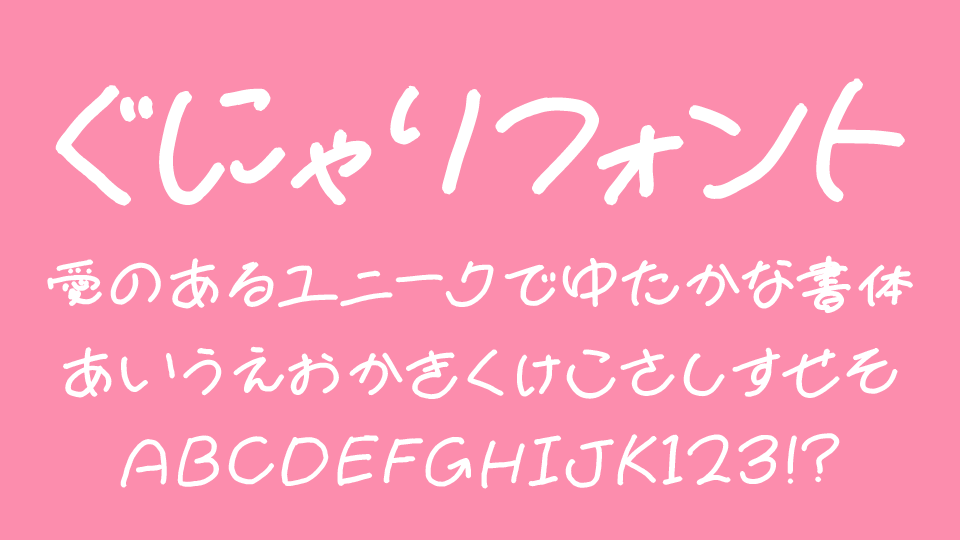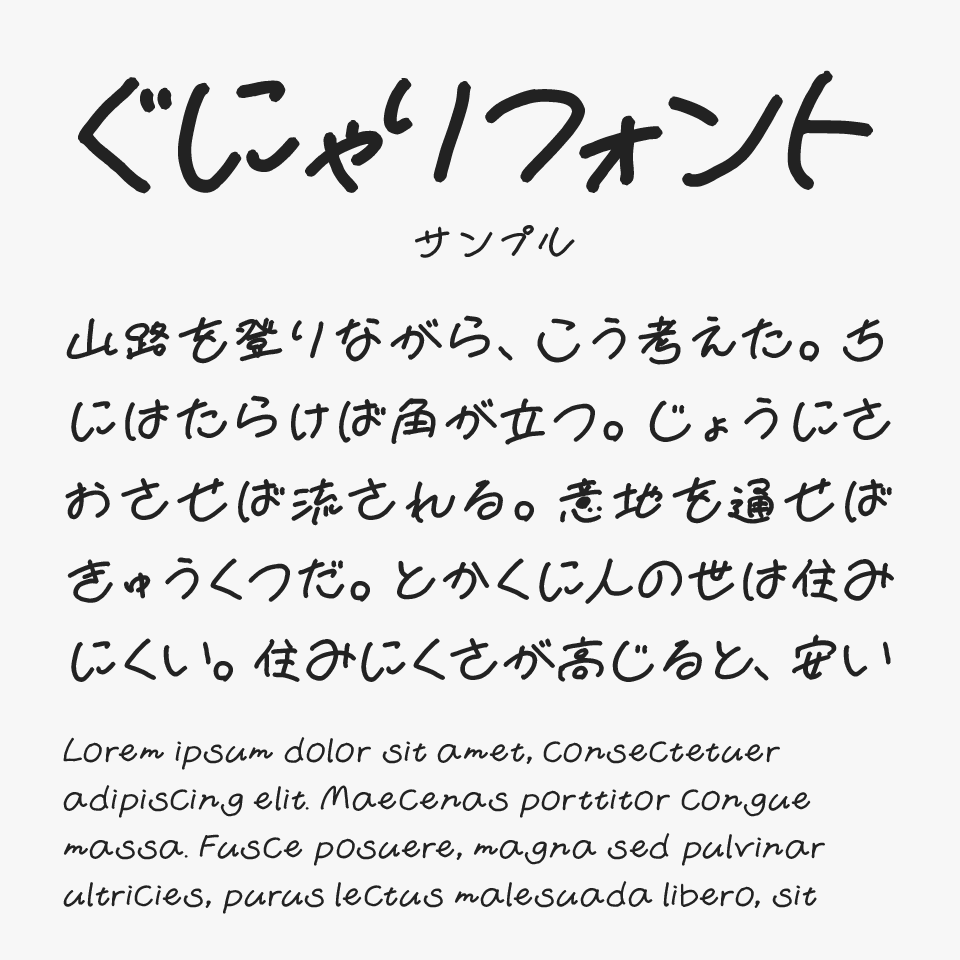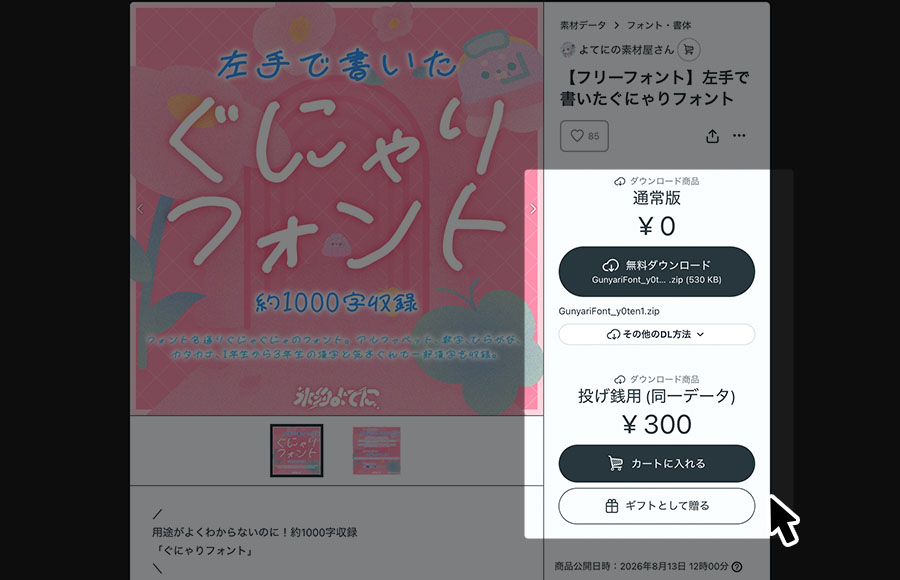
ぐにゃりフォント
ぐじゃりフォントは、左手が書いたぐにゃっと書いたようなラフさと、少し力の抜けたゆるさが可愛い手書きフォントです。
丸みのある文字に、線の揺らぎや文字ごとの大きさに自然なばらつきがあり、気取らない雰囲気をそのまま文字にしたような親しみやすさのある手書き文字です。
読みやすさを保ちながらも手書きらしい個性がしっかり感じられるため、肩の力を抜いたデザインによく馴染むフォントです。
SNS投稿やブログ、YouTubeサムネイル、手書きPOP、メッセージカードなど、親近感のあるデザインにぴったりなフォントです。かしこまりすぎない雰囲気を出したい場面や、日常感のあるデザインとも相性よく使えます。
| 収録文字 | 漢字・ひらがな・カタカナ・英数字・約物・記号 |
| 漢字の収録数 | 〇 (1,000文字程度) |